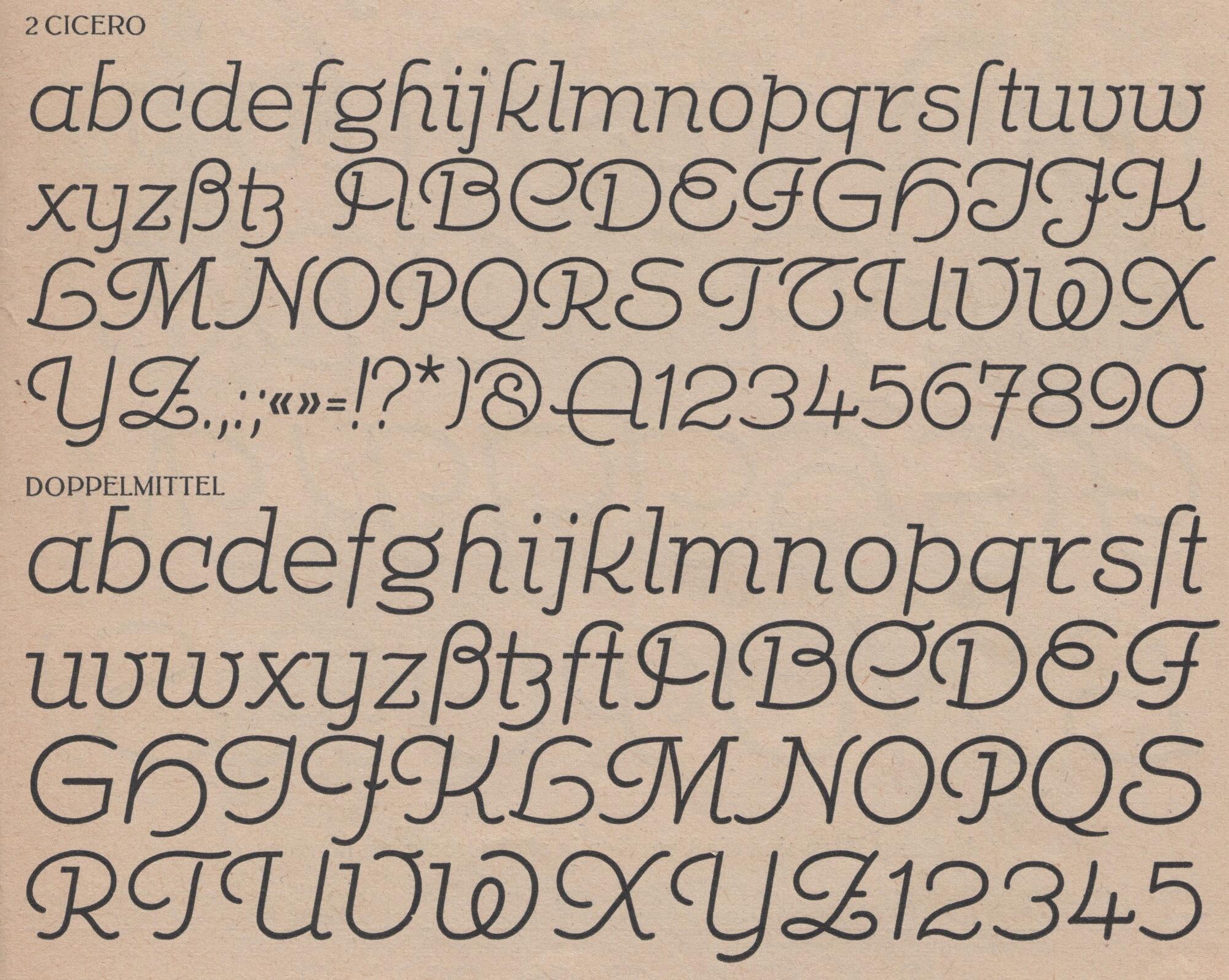
Font-Wiki: Zirkularschrift Korso
• 1913
• Antiqua Schreibschrift
Die (Zirkularschrift) Korso von F. Schweimanns erschien um 1913 bei der Schriftgießerei D. Stempel AG in einem Schnitt. Passende Zierversalien, Ornamente und Vignetten waren ebenfalls erhältlich.
Für die Intertype gab es später eine Variante unter dem Namen Camera.
Eine digitale Version von Coen Hofmann ist unter dem Namen Marli erhältlich.